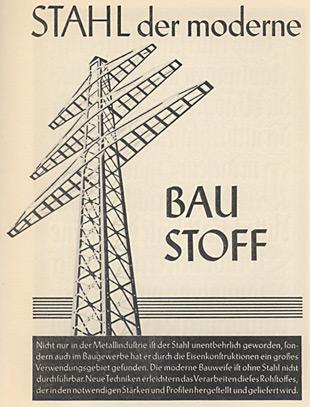
Die allgemeine Meinung (hier zum Bespiel vertreten von Der_Schwabe) ist, dass die Leute immer schlechter lesen und schreiben können, und das immer mehr typografische und Rechtschreibfehler auftreten.
Ich bin mir da nicht sicher, und wollte mal eure Meinung hören:
Wenn man sich eine gewöhnliche Tageszeitung von etwa 1900 ansieht, wird man feststellen, dass es dort von Rechtschreib- und Typofehlern, gerade in den Anzeigen, nur so wimmelt. Das gilt auch, in beschränktem Maße, für Schilder, soweit man diese auf alten Fotos sehen kann.
Und weiter: Heutzutage gehen mehr als ein Drittel der Schüler auf das Gymnasium; viele dann weiter auf die Universität. Es macht schon einen großen Unterschied, ob nur hellsten Köpfe (z.B. 5 %) einer Generation ein Studium aufnehmen oder ein Viertel der Bevölkerung. Im letzteren Falle wird man immer, unabhängig von veränderten Lehrformen usw., ein Nachlassen der Durchschnittsleistung feststellen können.
Zudem: Bis vor vierzig, fünfzig Jahren hatten viele Menschen einen Arbeitsplatz, der keinerlei Schreib- und oft auch keine Lesetätigkeit erforderte. Allein die ganzen Hilfskräfte in der Landwirtschaft, die es heute nicht mehr gibt, brauchten die Fähigkeit des Schreibens nicht. Diese Menschen waren teilweise sehr ungelenk im Schreiben (seht euch mal Feldpostbriefe aus dem Ersten Weltkrieg). Heutzutage muss (fast) jeder schreiben können, und man erwartet einen guten Standard.
Internet: Das Internet hat, meiner Meinung nach, zu vermehrtem Schreiben und Lesen geführt. Analphabeten können das Internet nicht nutzen. Wer eine Internetseite haben will, muss schreiben können. Das hat das Schreiben zu einem Massenphänomen gemacht. Wenn jeder schreibt, wird es natürlich viel mehr Fehler geben, als wenn nur hochgebildete und intelligente Menschen schreiben, die viel Übung haben.
Inflation der Drucksachen: Druck- und Satzkosten sind in den letzten Dekaden enorm gefallen. Heute kann (fast) jeder zuhause Drucksachen in einer ziemlich professionellen Qualität erstellen. Dass der Zivi auf dem Pfarramt aber nicht die gleichen Standards hat wie ein ausgebildeter Setzer, ist klar. Früher wurden eben die wenigen und teuren Drucksachen von gelernten Menschen produziert, heute handelt es sich um Massenware, mit allen Vor- und Nachteilen.
Um kein Missverständnis zu erwecken: Ich finde Rechtschreib- und Typofehler schlimm, und manchmal dreht sich mir der Magen beim Ansehen einiger idiotischer Fehler um. Ich habe auch wenig Verständnis für die Leute, die trotz eines unzureichenden Wissens meinen, Firmenschilder und gewerbliche Drucksachen produzieren zu müssen.
Aber: Ich glaube nicht, dass die Schreib- und Lesekultur "den Bach runter geht".
Gestern abend: Der krosse Deutsch-Test auf RTL. Erwartungsgemäß war – trotz des Themas – die Typografie schlecht wie immer. Mal abgesehen davon, dass die völlig unnötige Versalschreibweise wieder Millionen Deutschen eingebläut hat, dass man jetzt immer Doppel-S statt Eszett schreibt: Der Titel-Grafiker hat wie immer frei auf Koppelungsstriche verzichtet und mit Zollzeichen um sich geworfen.
Wie genial ist das denn? Zoll, dann aber von Hand nach oben und unten geschoben? Phantastisch. Irgendwie schon fast rührend gut gemeint, oder?
Und... wenn das die ErikRighthand ist, dann gibts da auch Small Caps, die deuuuutlich schöner sind als die Versalversion, die wir hier sehen.
Abgesehen davon finde ich einen großen Deutsch-Test aus-ge-rechnet bei RTL irgendwie schon richtig superklasse. Warten wir auf den großen Mathe-Test bei RTL II.
Die Zuschauerfrage beweist aber irgendwie, daß die Zuschauer es auch mal so rrrrrrrrrichtig nötig haben :-D.
Eingesandt von Peter Mettin, Bonn:
Bild 1 ist von einem namhaften Sportschuhersteller. Sie werden den Fehler sicher finden. Die unfreiwilligen Wortschöpfungen finde ich fast schon kreativ.
Bild 2 zeigt einen beliebten Fehler, der für mich den mikrotypografischen Super-Gau darstellt: Ein Akzentzeichen als Pseudo-Apostroph. Dummerweise noch nicht einmal ein Akut sondern ein Gravis, das mit seiner von-links-oben-nach-rechts-unten-Richtung dem Apostroph am unähnlichsten ist.
Ziemlich traurig finde ich auch, daß Spiegel Online falsche Anführungseichenverwendet, zumal sich der Sitch vom Zollzeichen, daß die meisten leute eben aus Unwissen oder Faulheit eingeben, zum typographisch korrekten Anführungszeichen vollautomatisieren lässt.
Aktuell ein Faltblatt aus meinem Briefkasten von gestern.
Die „FIFA Fußball-Weltmeisterschaft Deutschland“ wird hier permanent mit Doppel-s geschrieben, obwohl sie ja wohlweislich nicht in der Schweiz stattfindet, wo man das ß abgeschafft hat. Vielleicht liegt‘s ja aber am Schweizer FIFA Präsident.
Immer wieder werden wissenschaftliche Arbeiten in so bescheidener Office-"Qualität" gedruckt, dass es mir um Blut, Schweiß und Tränen Leid tut, die in den Inhalt inverstiert wurden:
Regeln hin oder her, ich finde, zumindest im richtigen Kontext: Just do it.
ganz meine meinung. regeln sind dazu da, gebrochen zu werden. wer weiß, wie es richtig geht, hat auch das recht, im berechtigten kontext darauf zu sch..., na gut, zu pfeifen.